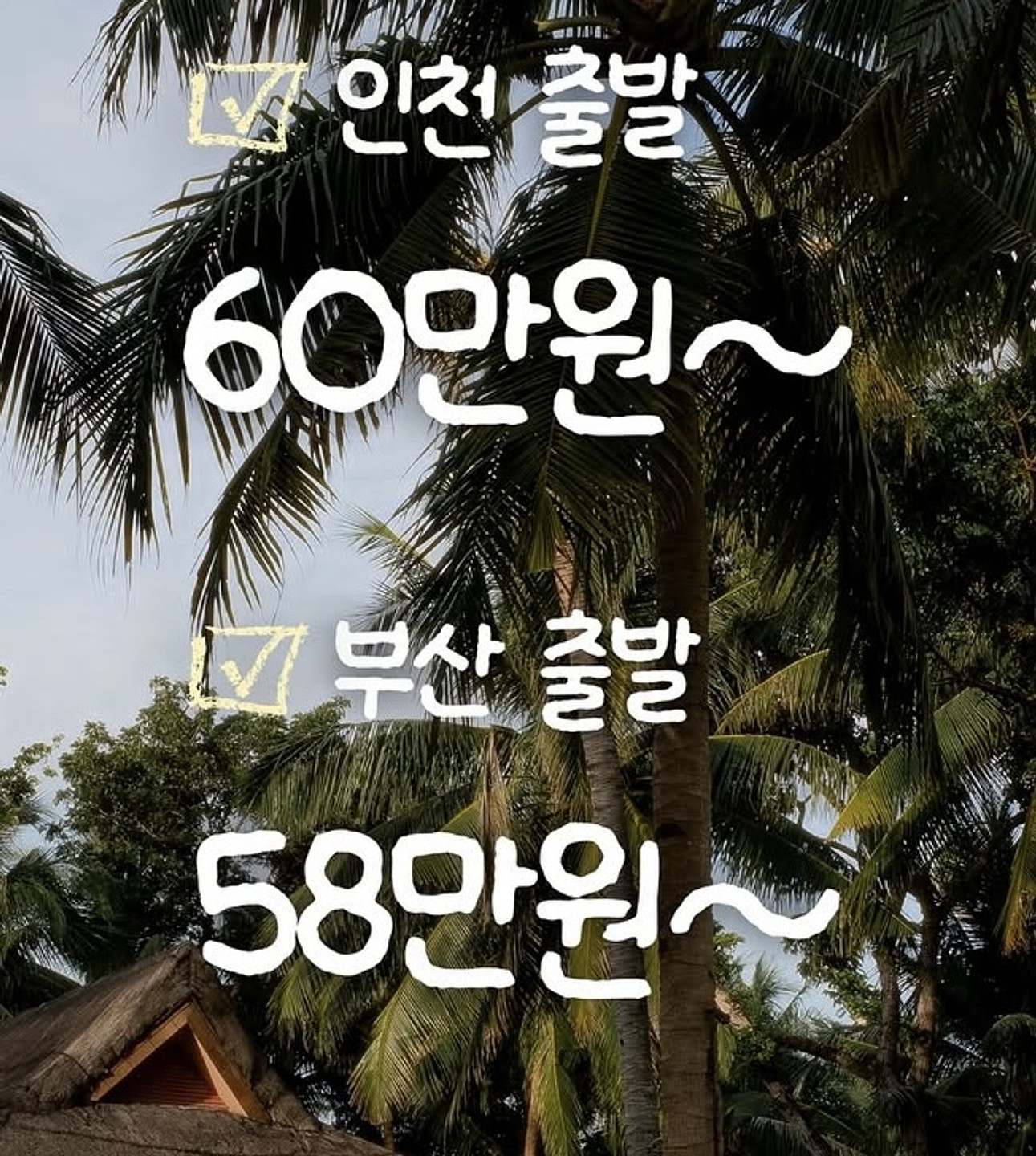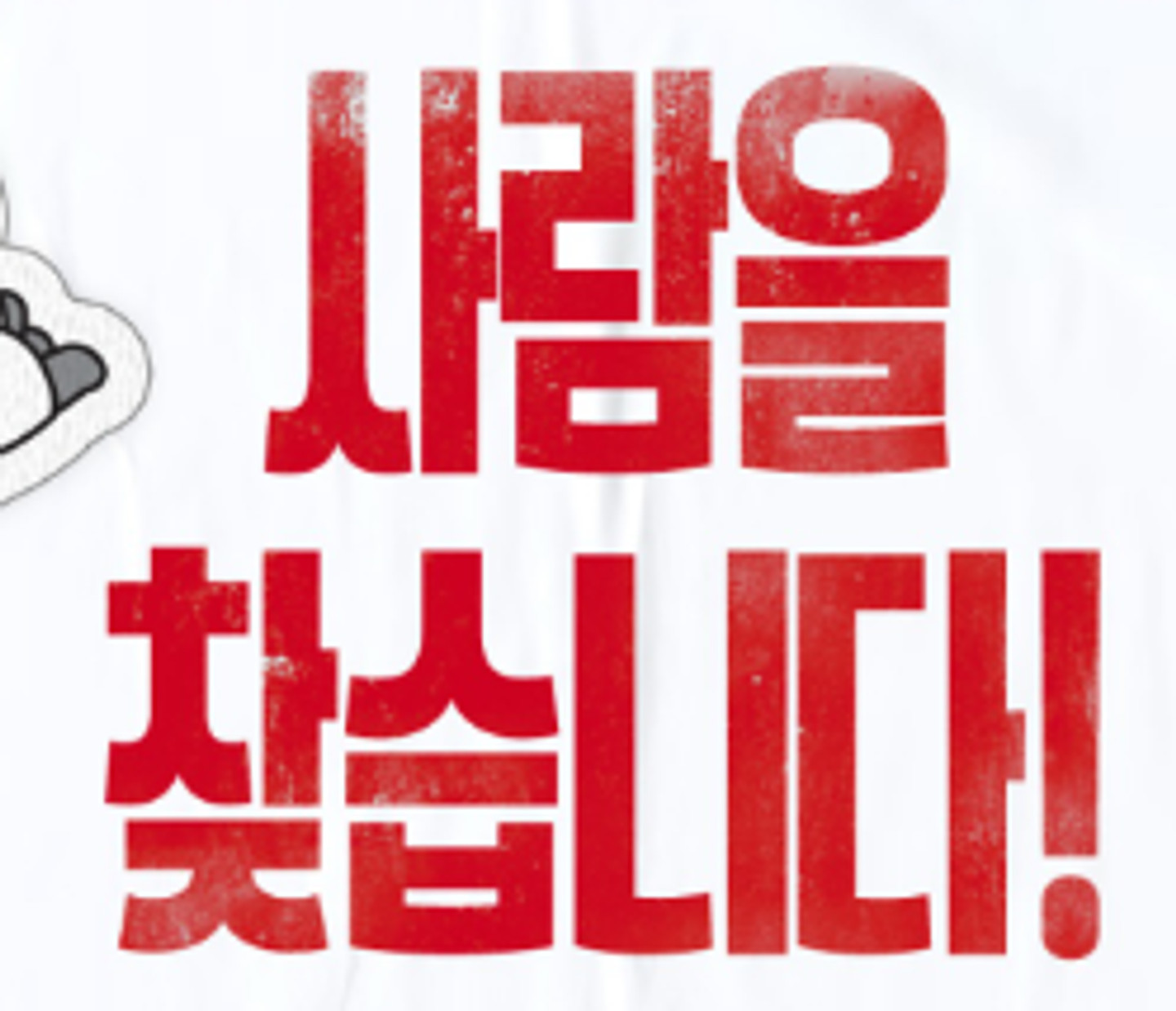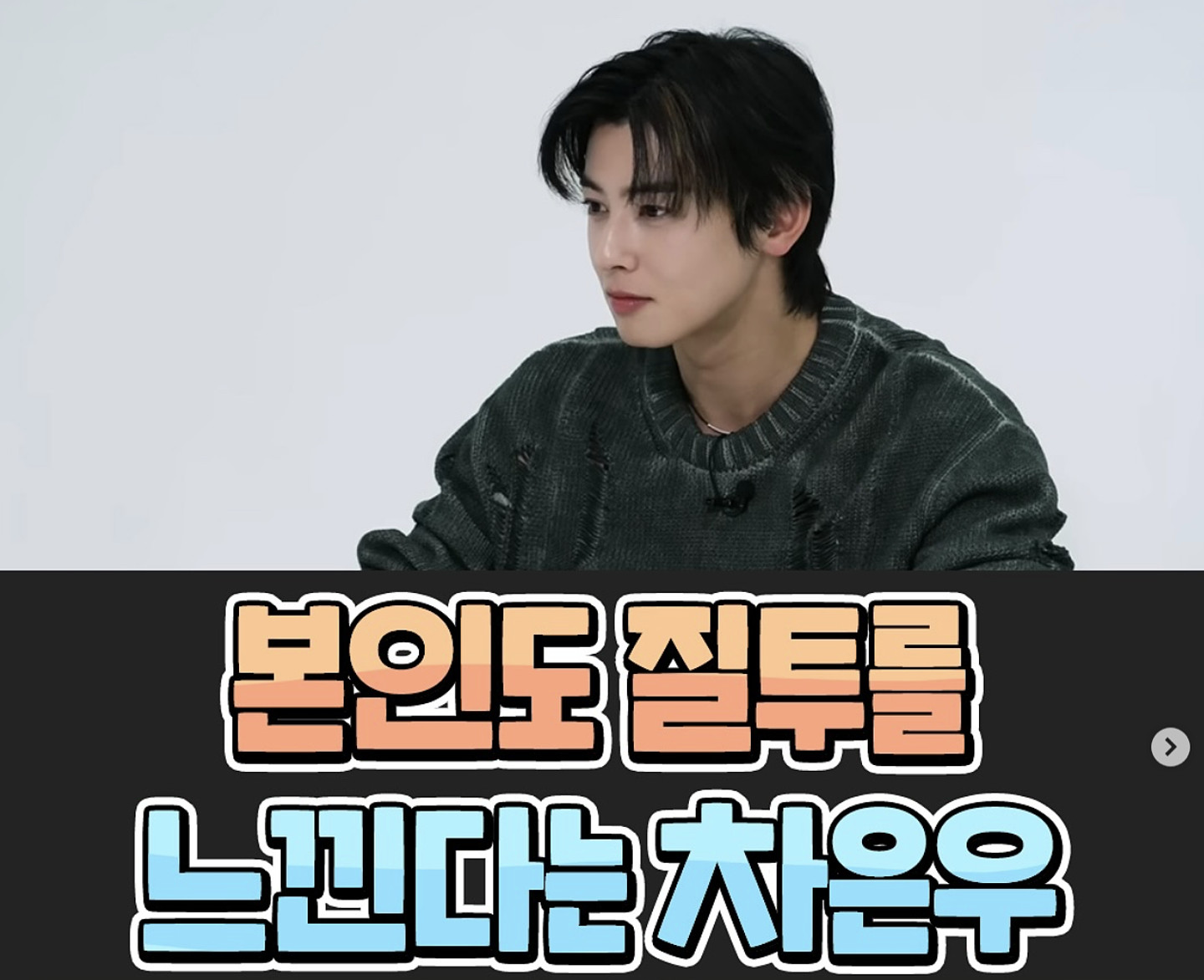
안녕하세요. 이거 유튜브에서 자막을 봤는데 너무 이쁘더라고요 그래서 어떤 자막인지 GPT랑 제미나이 두개 돌려봤는데 No to Sans 이게 가장 확률 높은거라고 해서 다운로드해서 해보니까 아닌거 같더라고요 ㅠ 어떤 서체인지 궁금하고 외곽선이랑 뒤에 그림자 효과까지 준거같은데 어렵네요 ... 이뻐보이는데
이 폰트 뭔가요 조선굴림체랑 ~ 물결 모양이 좀 다릅니다.. 정말 궁금해요 ㅠㅠ 카더정원이나 찰스엔터가 주로 사용하는 자막 폰트 같습니다
김부장 이야기 포스터에 사용된 폰트가 궁금해요. 글자마다 사이즈를 커스텀하신것 같긴한데.. 기본 폰트가 어떤 폰트인지 궁금합니다 ㅠ